ゴシック体フォントは、ウェイトが太くものを使えばしっかりインパクトがあるタイトルになったり、細いウェイトを使えばクールでかっこいい印象などのトーンを出したいときにも重宝する書体です。使うフォントやウェイト(太さ)によって全然印象が変わってくる超定番の書体の1つです。
Noto Sans
Noto Sansフォントは、GoogleとAdobeが協力して開発したベーシックな角ゴシック体フォントです。
定番なベーシックな角ゴシックフォントを探してる方はまずは「Notosans」から入れるのをおすすめです。ウェイトも7種類あり、非常に使いやすい角ゴシックフォントです。
M PLUS(M+)
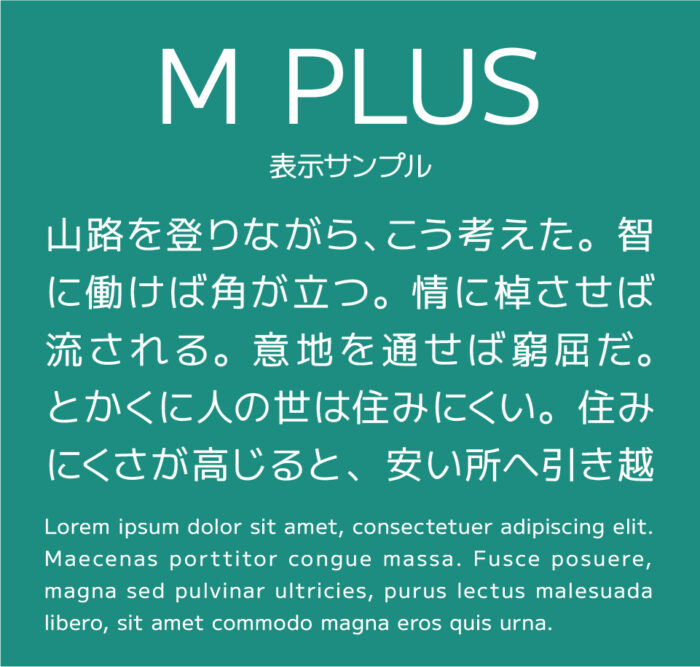
M PLUS(M+)フォントは、直線と曲線のメリハリがきいて、かな文字には丸みがあるので柔らかい印象のある、使いやすいモダンな角ゴシック体フォントです。
こちらも定番の角ゴシックフォントの1つで、ウェイトが9種類用意されているので、使いやすい角ゴシックフォントです。
つなぎゴシック
角を丸く加工し、墨だまり処理を加えられたゴシック体のフォント。
角丸加工が柔らかな印象をあたえ、こぶりなひらがな・カタカナのデザインも柔らかく優しい雰囲気をもたせているフォントです。
モボ
やわらかくレトロな雰囲気にしたフォントです。
太さもありインパクトが強いフォントですが、文字の角が丸く処理されている柔らかい印象になっており、タイトルや見出しなどにもピッタリなフォントです。
なごみ極細ゴシック
全体的に超極細のラインでデザインされているフォントです。
モダンで直線的なデザイン、と対照的に懐が狭くオールドスタイルなかなデザイン、他にはないような二つのスタイルが合わさっているユニークなゴシック体フォントです。
資料などスタイリッシュな印象にしたいにタイトルなどに使うと良いかもしれません。
LINE Seed JP
チャットアプリなどを開発している「LINE」のコーポレートフォントとして開発された日本語書体フォントになります。いい意味でクセが少なくスタンダードなゴシック体です。
LINEの従来のイメージを保つために、親しみのある角丸ゴシックながら大人なモダンな印象があり、豊富なウェイトも使うことができるのでデザインや資料作成などでも活用できるかと思います。
さわらびゴシック
スタンダードなゴシック体の日本語フリーフォントです。可読性に優れており、サイズが小さくても文字がはっきりして見えるため、さまざまなデザイン制作や施作成に重宝するフォントです。
コーポレート・ロゴ
フォント「コーポレート・ロゴ」はその名の通りに企業やサービスのロゴとして使えるように少し縦長になっており、モダンな雰囲気のゴシック体フォント。角張っておりいい意味でのクセが、ロゴとしても使いやすいフォントになっているかと思います。
BIZ UDPゴシック
ユニバーサルデザインのゴシックフォントになります。フリーで使えるUDゴシックフォントはなかなか見当たらないので、とても貴重なフォントかと思います。
ユニバーサルデザインとは、誰にとっても分かりやすく、読みやすいように考えられてフォントになります。
UD(ニバーサルデザイン)フォントなので、デザイン制作のタイトルから本文まではもちろん、資料制作、プレゼン資料などで幅広く活用できること間違いないです。
せのびゴシック
オープンソースで定番の「M+ FONTS」を機械的に70%のコンデンスド風(長体風)に加工し、オリジナルのかなを組み合わせたフォントです。
コンデンスド(長体)になることで、無機質でクールなフォルムなのでテクノ・未来的なカッコいい印象なゴシックになっています。
かんじゅくゴシック
熟成された味わいとレトロな雰囲気が魅力のフォントになっています。
製作者いわく「ガタガタとしたラフなラインが味わい深いロゴ・見出し用のデザインはまさに完熟。このフォントを活用すれば、あなたのサイトや印刷物に深い味わいとコクをもたらすでしょう」とのことです。
やさしさゴシック
上記のサンプル画像を見ていただくとわかるかと思いますが、ゴシック体ですが、全体的に少しこぶりで丸みや手書き風のような親しみ感や優しさを感じられるフォントです。
漢字も豊富に揃っており、文字の可読性も非常に優れていますので、デザインシーンだけではなく、資料作成やプレゼンなど幅広いビジネスシーンで活躍できるフォントです。
鉄瓶ゴシック
極太のゴツゴツとした質感の味わい深い一風変わったフォントです。ゴシック体ながら、少し手書きっぽい温かみを感じることができるユニークな印象があるフォントです。
パワフルなウェイトに太さがあるので、タイトルや見出しに使うことインパクトがでること間違いなしです!
夏蝉丸ゴシック
オープンソースのZen角ゴシックAntiqueを角丸加工した仮名とZen丸ゴシックを合成して作られた、レトロな雰囲気が特徴の丸ゴシック体です。
ある程度太いウェイトなので、見出しやキャッチコピーにも向いているフォントです。可愛いですね。
スマートフォントUI
スマートなデザインを実現するために約90%のコンデンスド(長体)になっておりスタイリッシュな印象のゴシック体フォントです。
Webデザインやアプリなどのスクリーン・デバイス上での見栄え・UI等での読みやすさを重視してデザインされているので、デジタルデザイン向けのタイトルや見出しに使用してもGOODです!
刻ゴシックフォント
スタンダードなゴシック体の漢字フォントに、それとは相反する字面の小さなひらがな・カタカナを合成したフォントになります。
上記のサンプルを見てもわかるように、漢字に比べてひらがな・カタカナを幅ごと小さくデザインされているフォントです。長文のように何行にもわたって組まれた文字列を眺めると、統一感のある美しさに気づかされます。
フォーク体フォントにも少し似ているフォントになっています。
きなりゴシック
かな文字は少し長体になっており、他のゴシックに比べ、角丸の処理や角張がやわかいカーブの処理がされているため、優しい雰囲気をもつゴシック体となっています。
しっぽり太ゴチック
しっぽり太ゴチックは、レトロな印象をもつ、伝統的なスタイルの太ゴシック体です。文字の交差部分には、墨だまりの加工が加えられていることで、温かみさや柔らかさを感じる素敵なフォントです。
しっぽり太ゴシック
しっぽり太ゴシックは、上記で紹介している「しっぽり太ゴチック」の文字を別バリエーションとして調整されている太ゴシック体です。